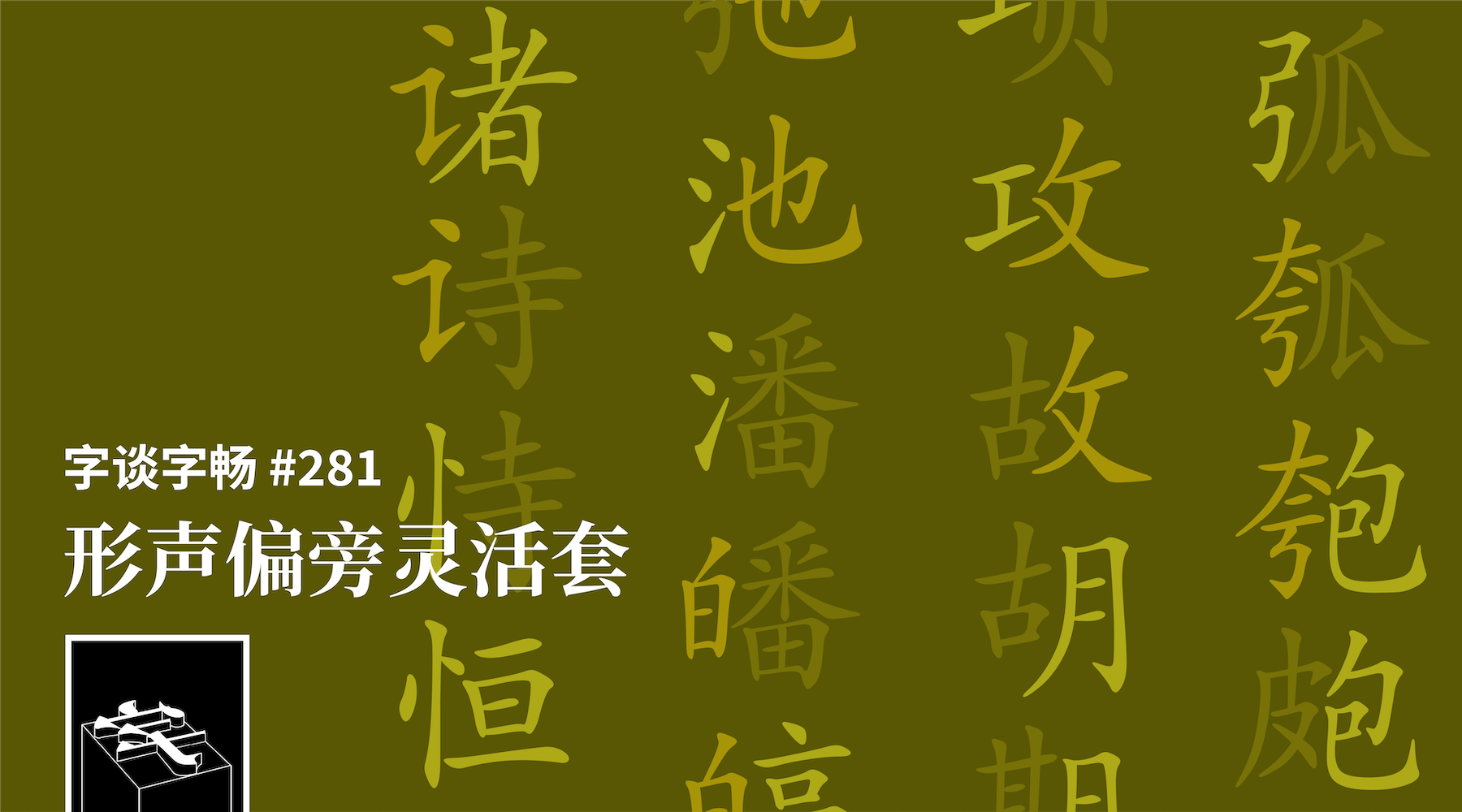
中文字体设计常需覆盖较大的字符集合,部件拆分及灵活套用是字体设计师们绕不开的话题。本期节目,嘉宾厉致谦将与我们一起回顾诸多前辈设计师的工作理念及实践方法。
- 徐學成(著).厲致謙、應寧(編著).《字耕一生:徐學成的故事》.三聯書店(香港)有限公司,2026 年
- 上海印刷技术研究所(原「上海印刷研究所」)
- 本顿雕刻机(Benton Pantograph),Linn Boyd Benton 发明的金属字模雕刻机,具备字形缩放等功能
- 小宫山博史著,孙明远译.《明朝体活字:其起源与形成》(明朝体活字—その起源と形成).江苏凤凰美术出版社,2025 年
- GF0014—2009《现代常用字部件及部件名称规范》将传统的「偏」「旁」「冠」「脚」的叫法改称某字「旁」「边」「头」「底」
- GF0011—2009《汉字部首表》在1983年《汉字统一部首表(草案)》的基础修改,定出 201个主部首,100 个附形部首
- 华康字型早在1987年即用笔画组字方法制作字体
- 三言出品的Glyphs插件「拆字小组」